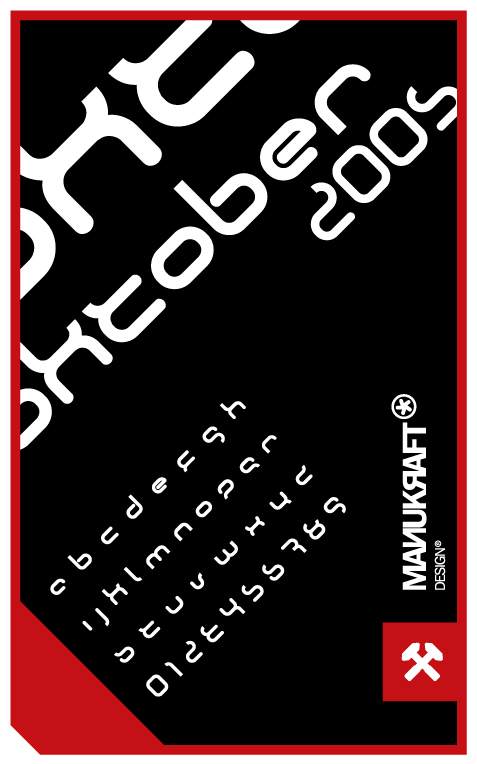
Oktober to darmowy, futurystyczny font typu display o zaokrąglonych, kwadratowych formach i ciasnych wewnętrznych krzywych, które nadają mu miękki, mechaniczny rytm. Litery opierają się na spójnej, modularnej strukturze z otwartymi narożnikami i płynnymi połączeniami, dzięki czemu cały alfabet wygląda bardziej technicznie niż dekoracyjnie.
Oktober świetnie sprawdza się w tytułach sci-fi, brandingu technologicznym, grafikach do aplikacji, plakatach, logotypach i krótkich tekstach promocyjnych, ponieważ jego kształty niosą ze sobą wyraźny, cyfrowy charakter bez ostrych krawędzi. Stabilny rytm i geometryczne krzywe czynią go również solidnym wyborem do banerów interfejsowych, oznakowań eventowych i opakowań, które wymagają eleganckiego, zakodowanego wyglądu.